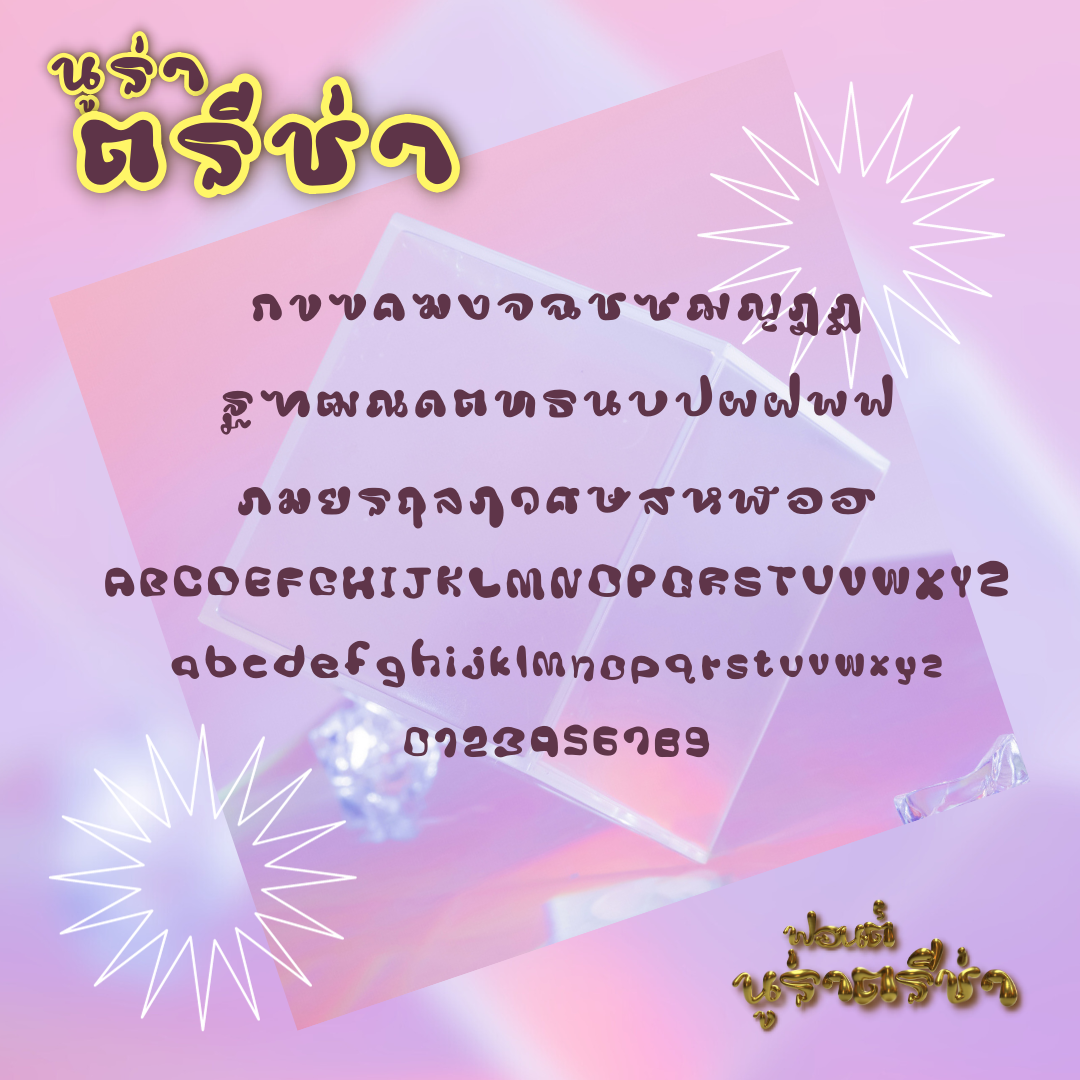
นูร่าตรีช่า (Nura teecha)
นูร่าตรีช่า  (Nura teecha)
ฟอนต์ลายมือน่ารัก ฟอนต์มีไม่หัว  ฟอนต์สองดีทำมาจากการปั้นทรีดี มีด้วยกัน 3 น้ำหนัก  คือ บาง ปกติ หนา